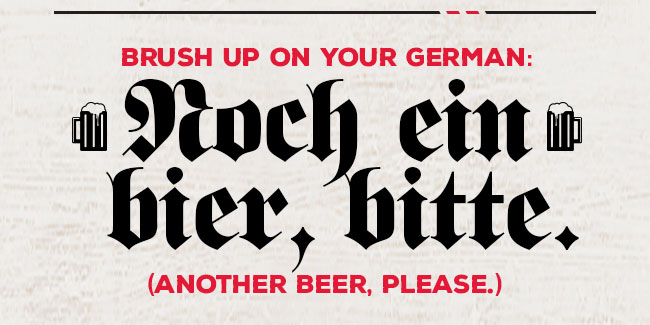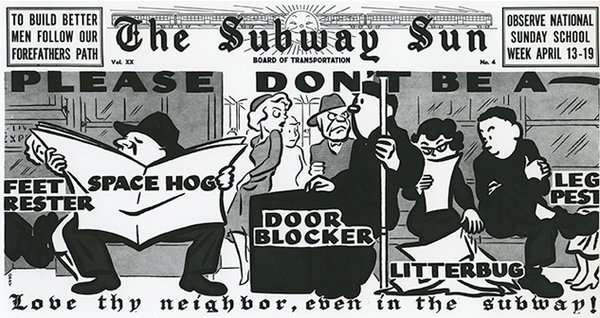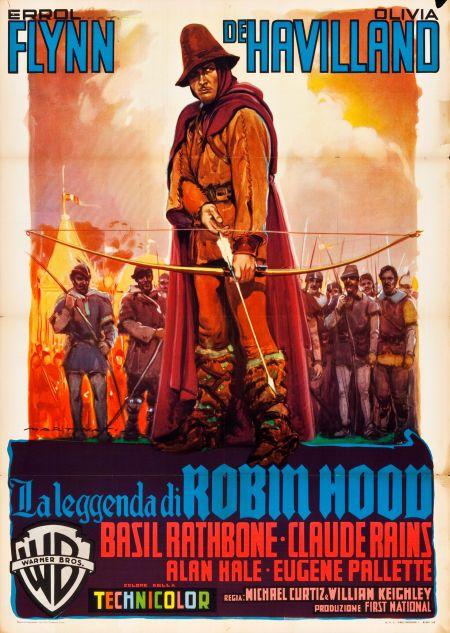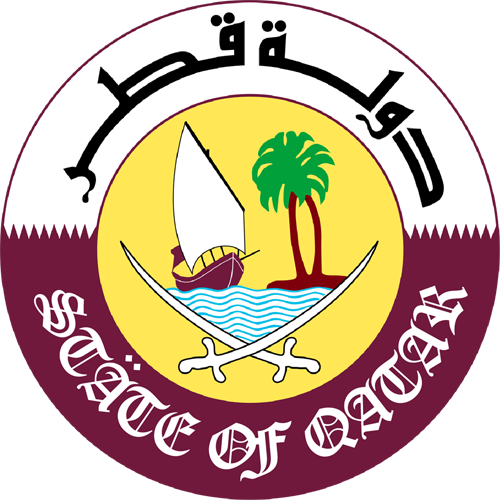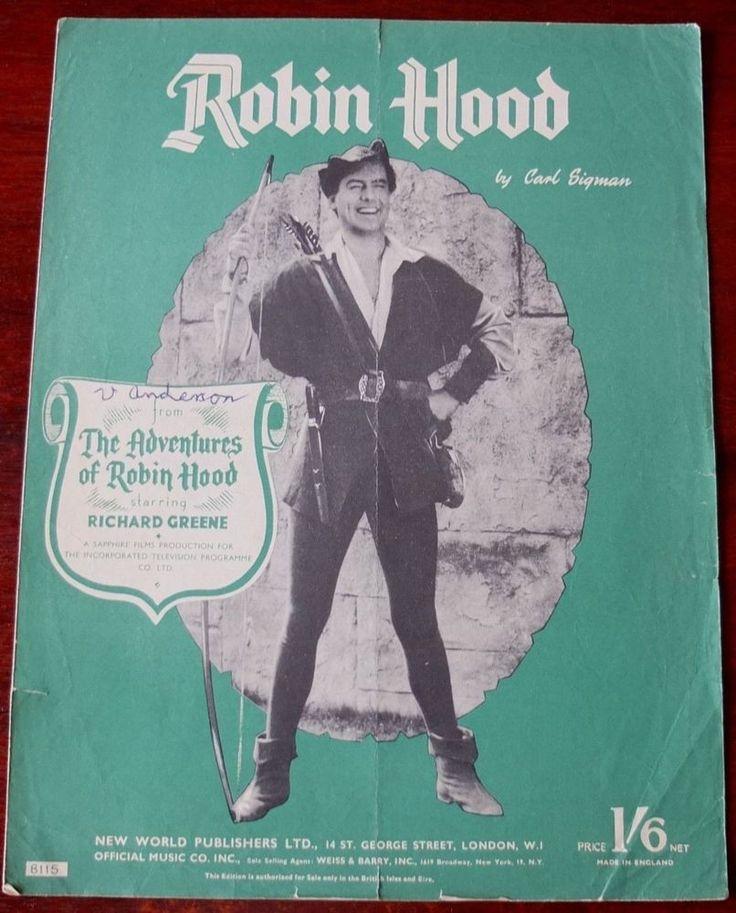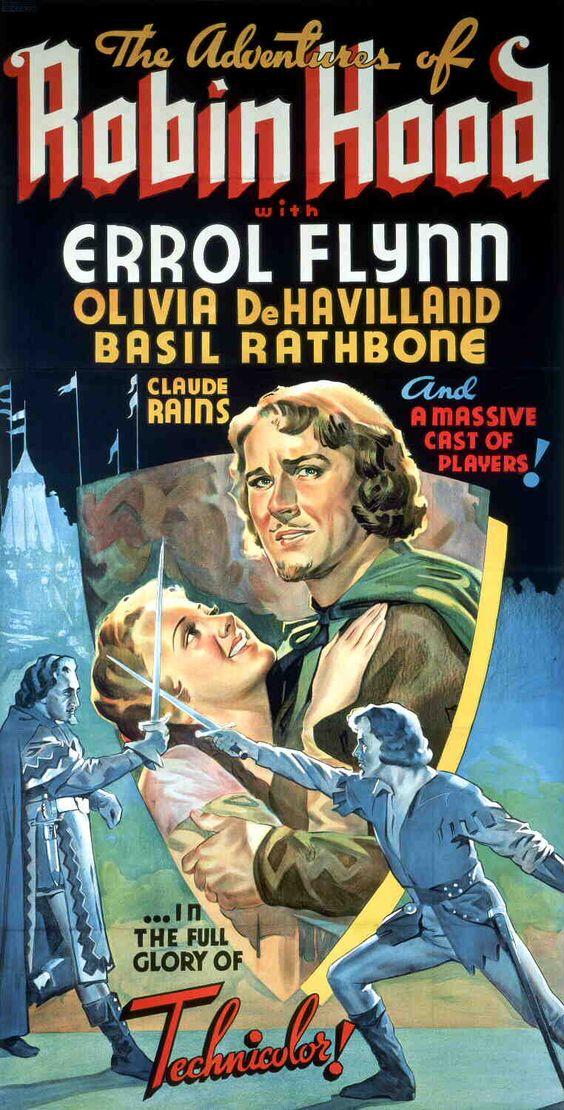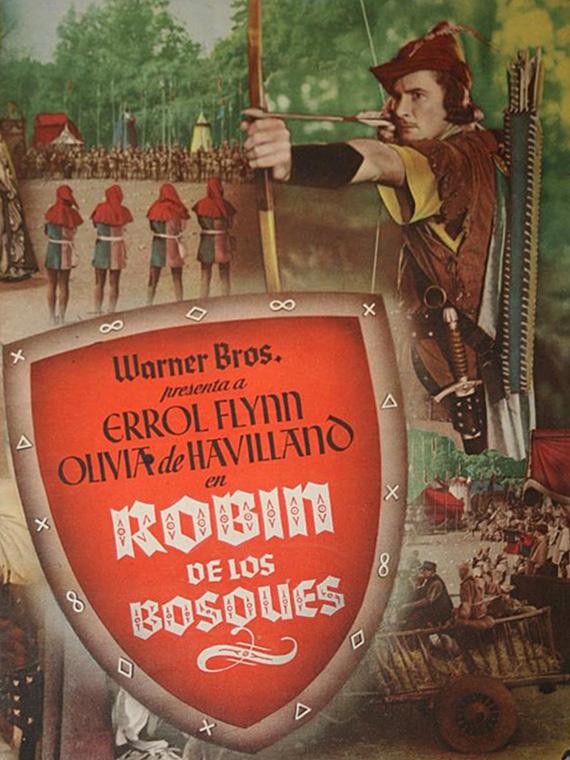
Gebrochene Schrift außerhalb des deutschen Sprachraums
Ist thy eigentlich ein gewollter Archaismus oder war das Pronomen zu der Zeit noch im Gebrauch?
Das ist ein gewollter Archaismus, und bezieht sich auf in der englischen Bibel Matthew 22:39 oder Leviticus 19:18
... Thou shalt love thy neighbour as thyself ...
Love thy neighbor ist halt eine feststehende Redewendung. Klar geht sie auf die Bibel zurück, aber das heißt nicht, dass, wer sie benutzt, bewusst archaisch reden oder schreiben will. Ich würde soweit gehen zu behaupten, dass die beste Übersetzung von »Liebe deinen Nächsten« eben “love thy neighbor” ist, nicht “love your neighbor”.
Ich würde soweit gehen zu behaupten, dass die beste Übersetzung von »Liebe deinen Nächsten« eben “love thy neighbor” ist, nicht “love your neighbor”.
zumindest so bis mitte der 70er war es nicht nur die vielleicht beste, sondern auch die gängigste übersetzung (in britischen texten ist es etwas unentschiedener) :tutor:
Hmm, was ist das Ziel dieses Threads? Es gibt massenweise historische, in Fraktur gesetzte Werke in Tschechisch, Slowakisch, Sorbisch, Lettisch, Norwegisch, Dänisch und vermutlich noch ein paar anderen Sprachen. Sie alle hier aufzulisten würde sicher den Rahmen sprengen.
Aus der aktuellen Werbung einer US-Gaststättenkette zur Oktoberfestsaison:
Die Betreffzeile der Email lautet: „Do you prefer bier or beer for Oktoberfest?“ und die erste Zeile der Nachricht: „We serve both.
Hmm, was ist das Ziel dieses Threads?
Ich dachte eigentlich, das sei offensichtlich: ungewöhnliche Beispiele zu sammeln. :baeh:
Ich habe nur mal eine einzelne Quizfrage für euch (die ich mir allerdings gut in einem Typografie-Trivial-Pursuit vorstellen könnte): Im offiziellen Wappen welches UNO-Mitglieds kommt gebrochene Schrift vor? Soweit ich nichts übersehen habe, gibt es genau eins.
jepp, vorallem aber hässlich und unpassend.
wahrscheinlich dachte man damals bei der übersetzung des emblems "welche internationale schriftart kommt unserer arabischen schrift am nächsten?"
Warum eigentlich nicht gleich in Gangsta-Rappa-Versalien, wenn schon Old English – würde auch zu Ölscheich mit Goldkettchen passen :-?:-|
Auch ich habe da etwas gebrochenes außerhalb des Deutschen Sprachraums gefunden.
Eigentlich hatte ich ja etwas gegen gebrochenes gesucht, und auf einer China-Seite einen günstigen Acryl 2-Komponenten-Kleber mit sehr kurzer Abbindezeit gefunden. Beim Markennamen des chinesischen Herstellers habe ich dann doch etwas dumm geschaut...
Robin Hood – Kommunist oder Nazi? Auf alle Fälle gebrochen! :mrgreen::-?
Film mit Errol Flynn, 1938, USA
sowie Serie mit  Richard Greene, 1955–1960, England.
Ich mag ja das Poster mit der geometrischen Schrift im Mix, erinnert irgendwie an Starwars.